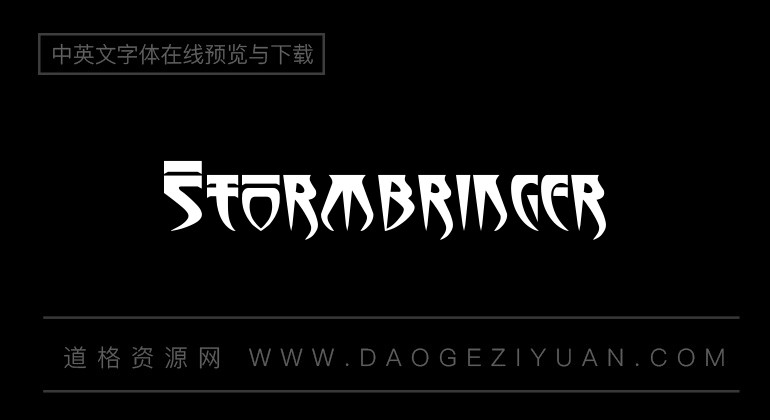
Stormbringer
? Stormbringer 字体是一种漂亮而粗犷的手写字体,它的特点是有着较宽的笔画,显得特别有力量感。它具有鲜明的线条,看起来有点粗犷,但是让它看起来更为精致。它可以用于多种用途,如标题、标签、海报等,可以让您的设计更加独特。
Stormbringer是一款非常不错的手写艺术字体,具有很好的视觉感,适合于文化类的宣传设计、商业类品牌的广告和产品包装设计以及个性化文字排版等较多场景。